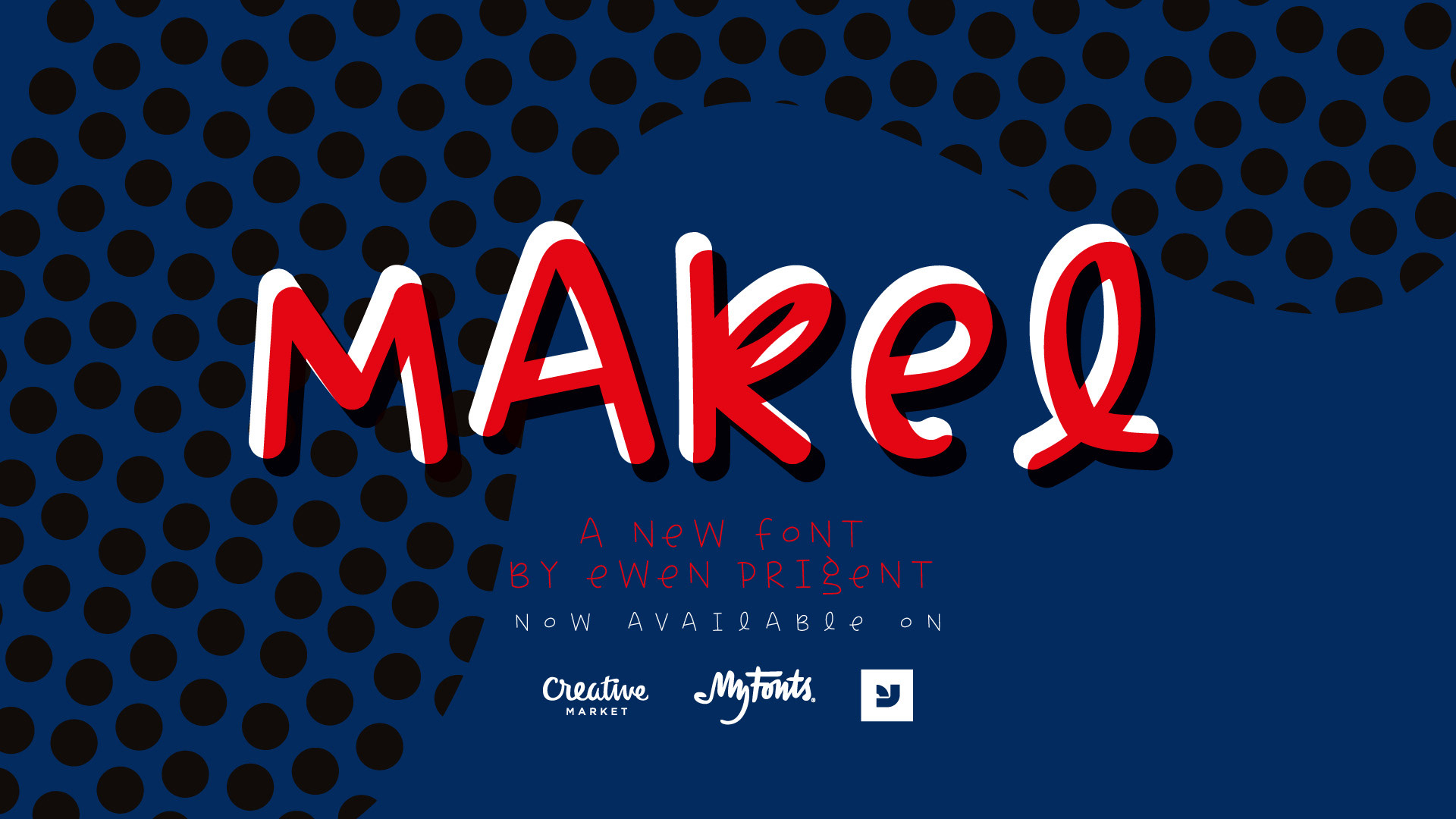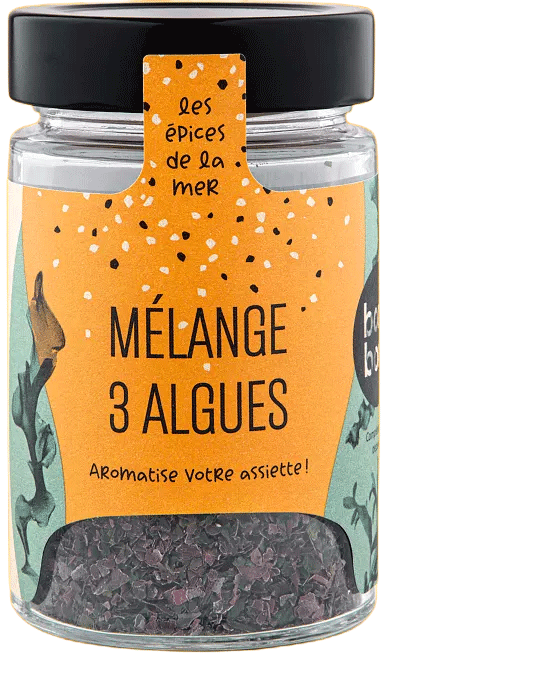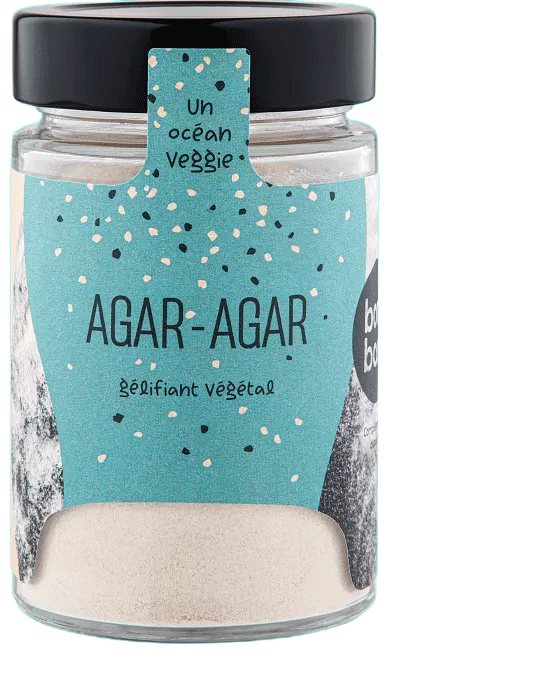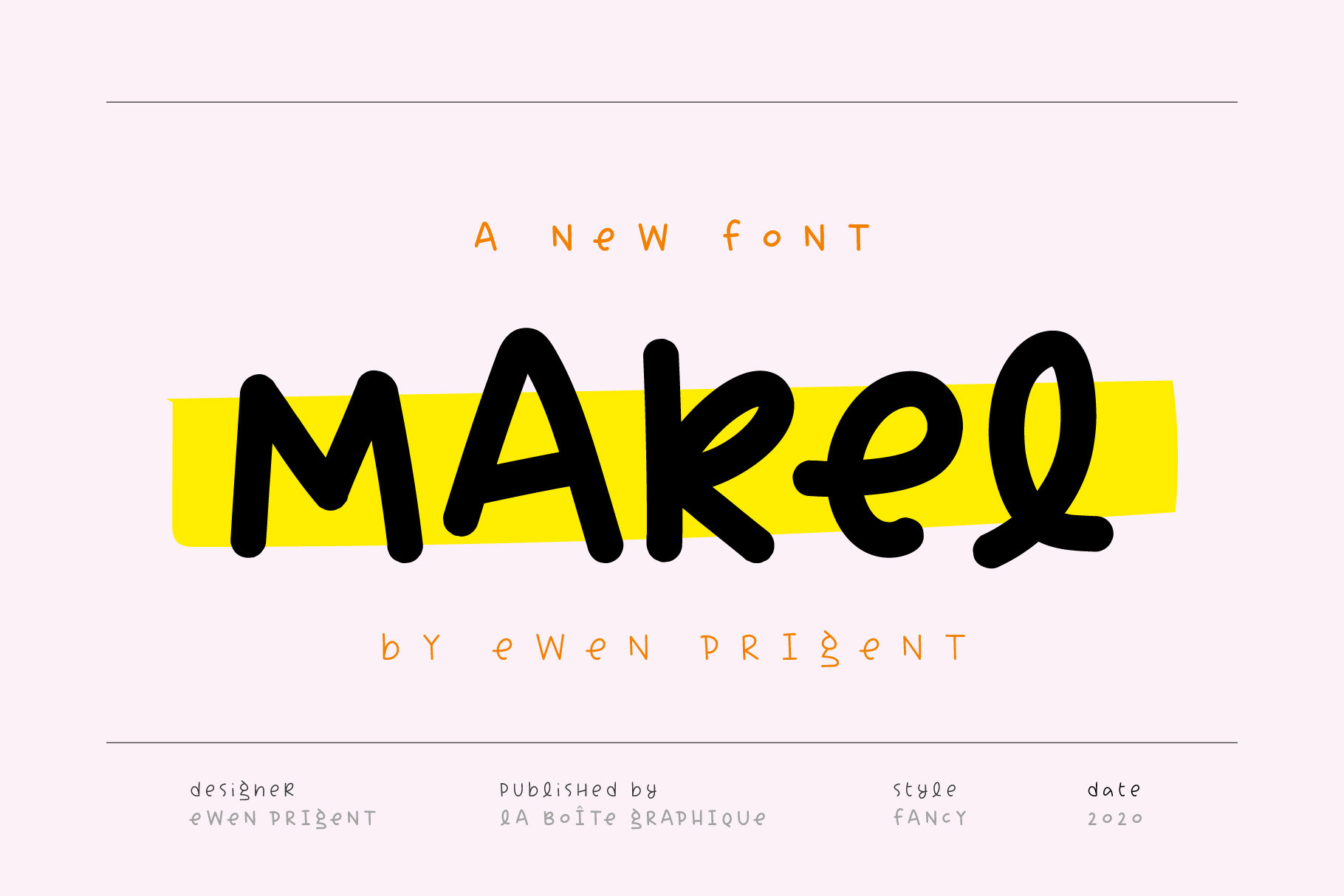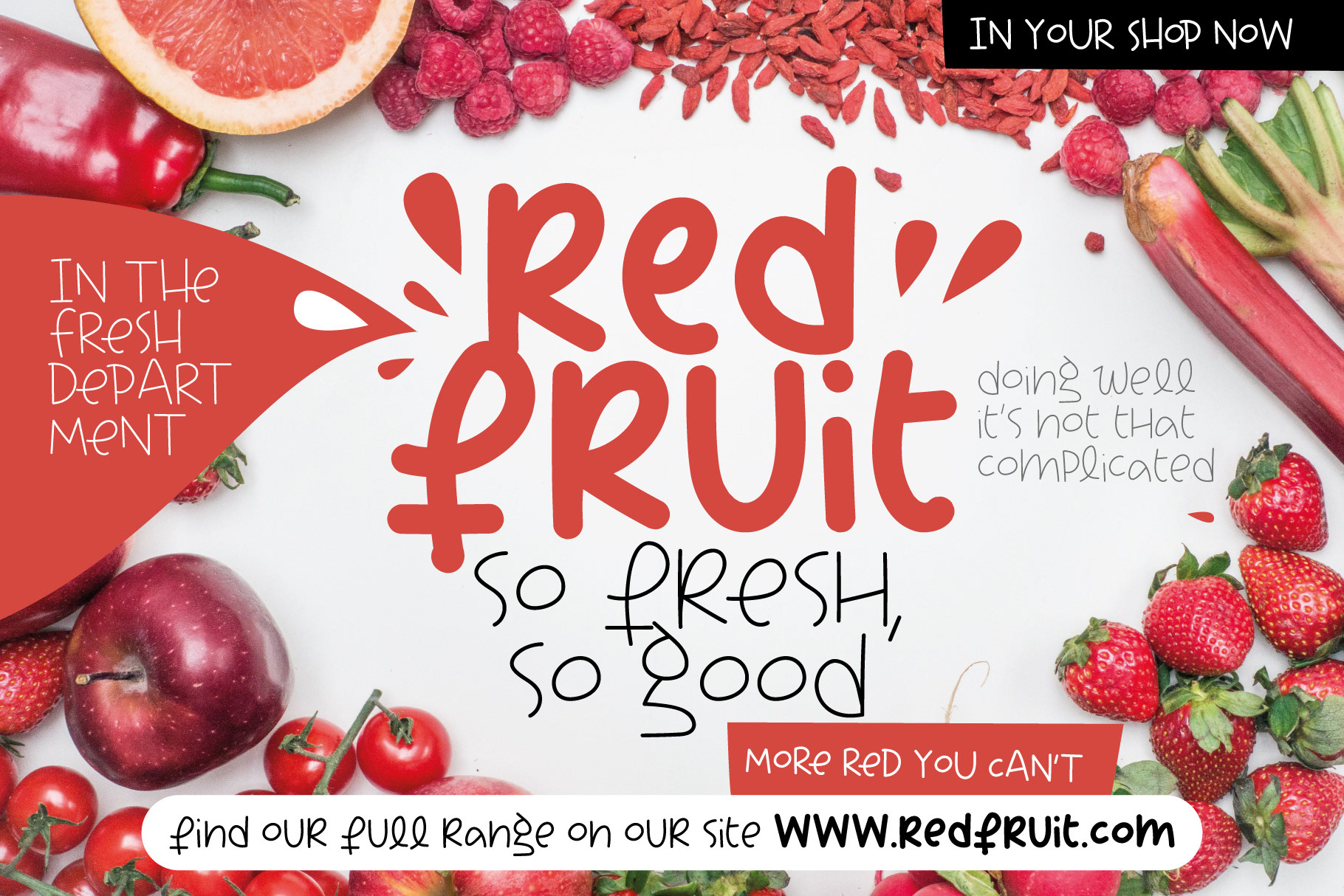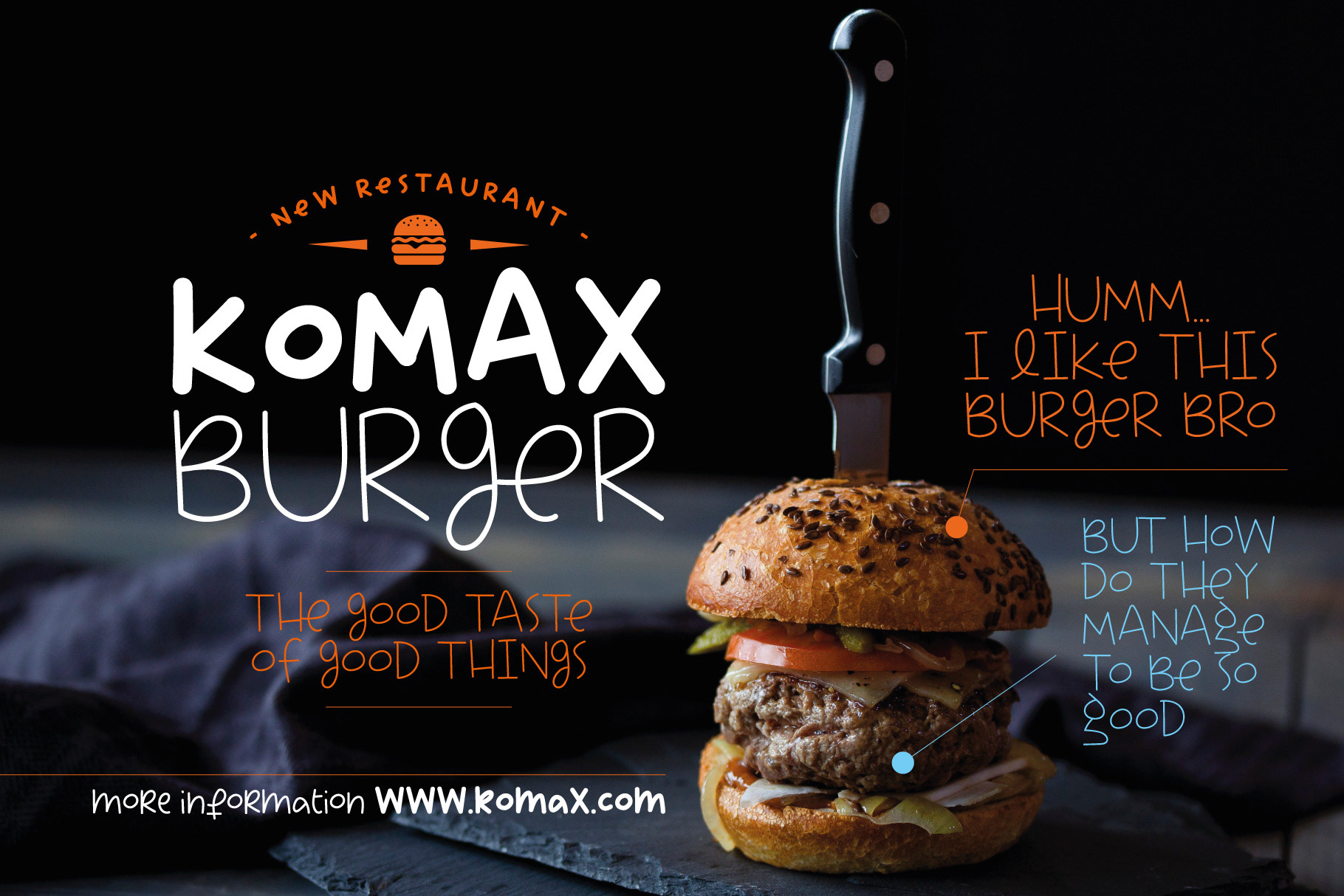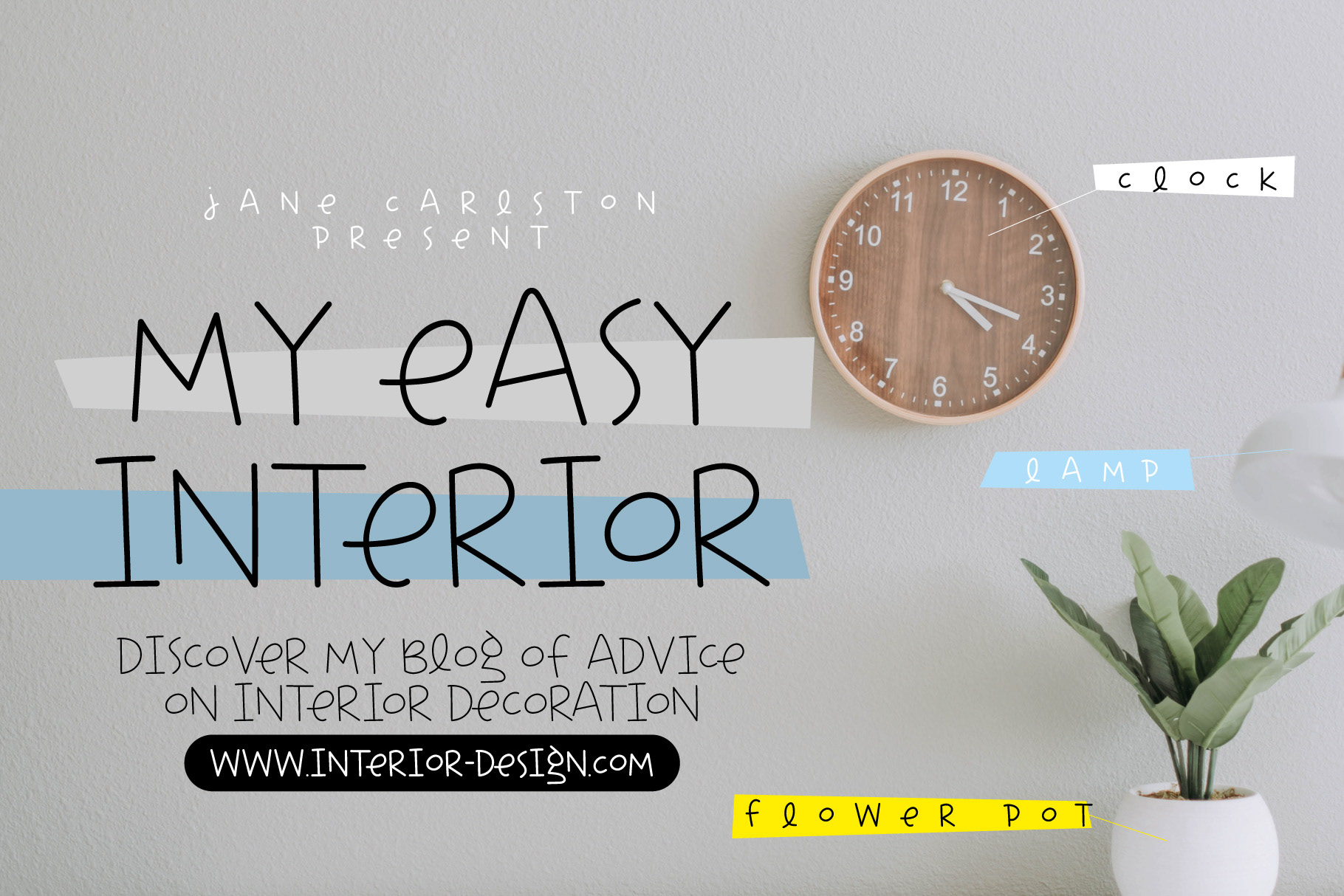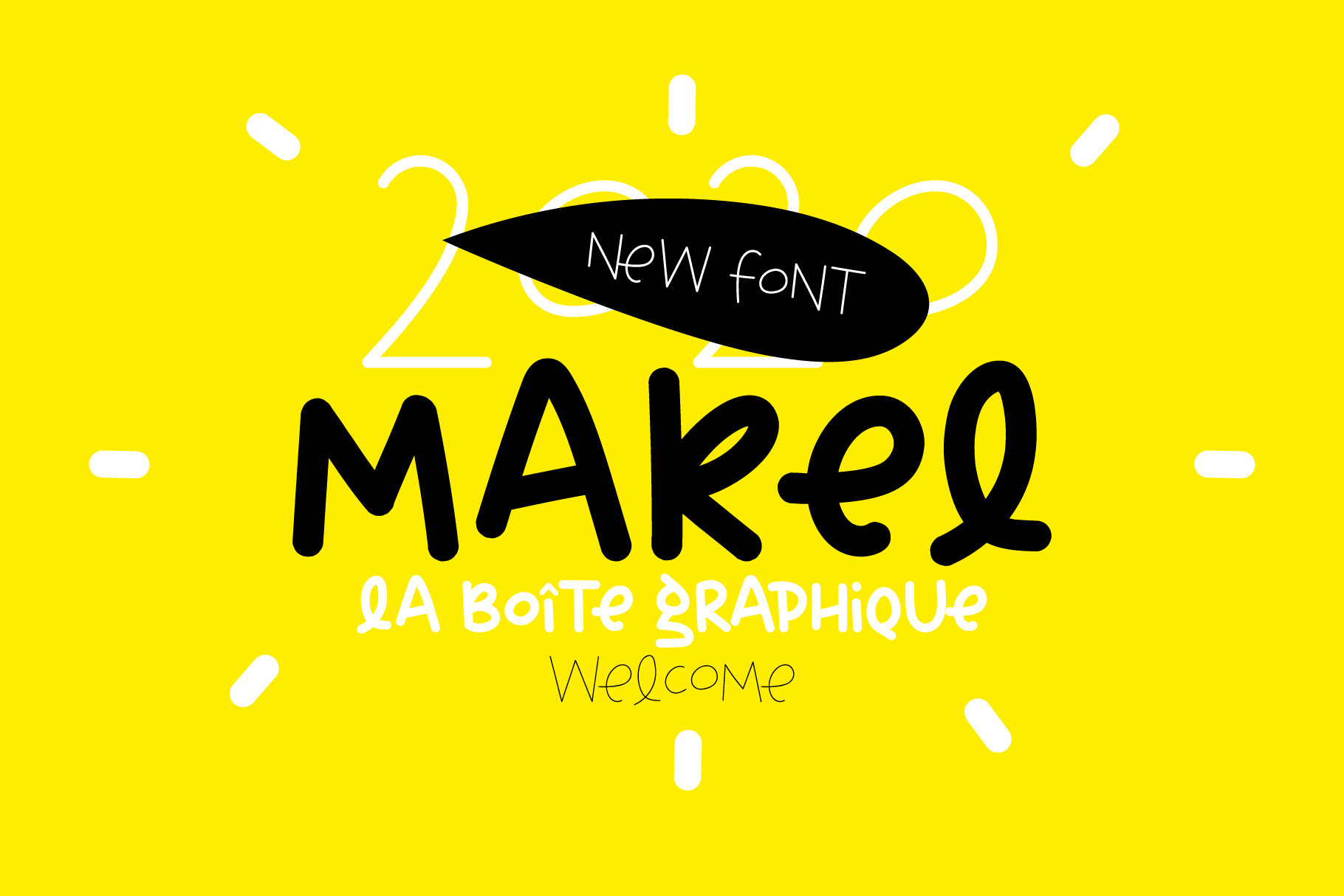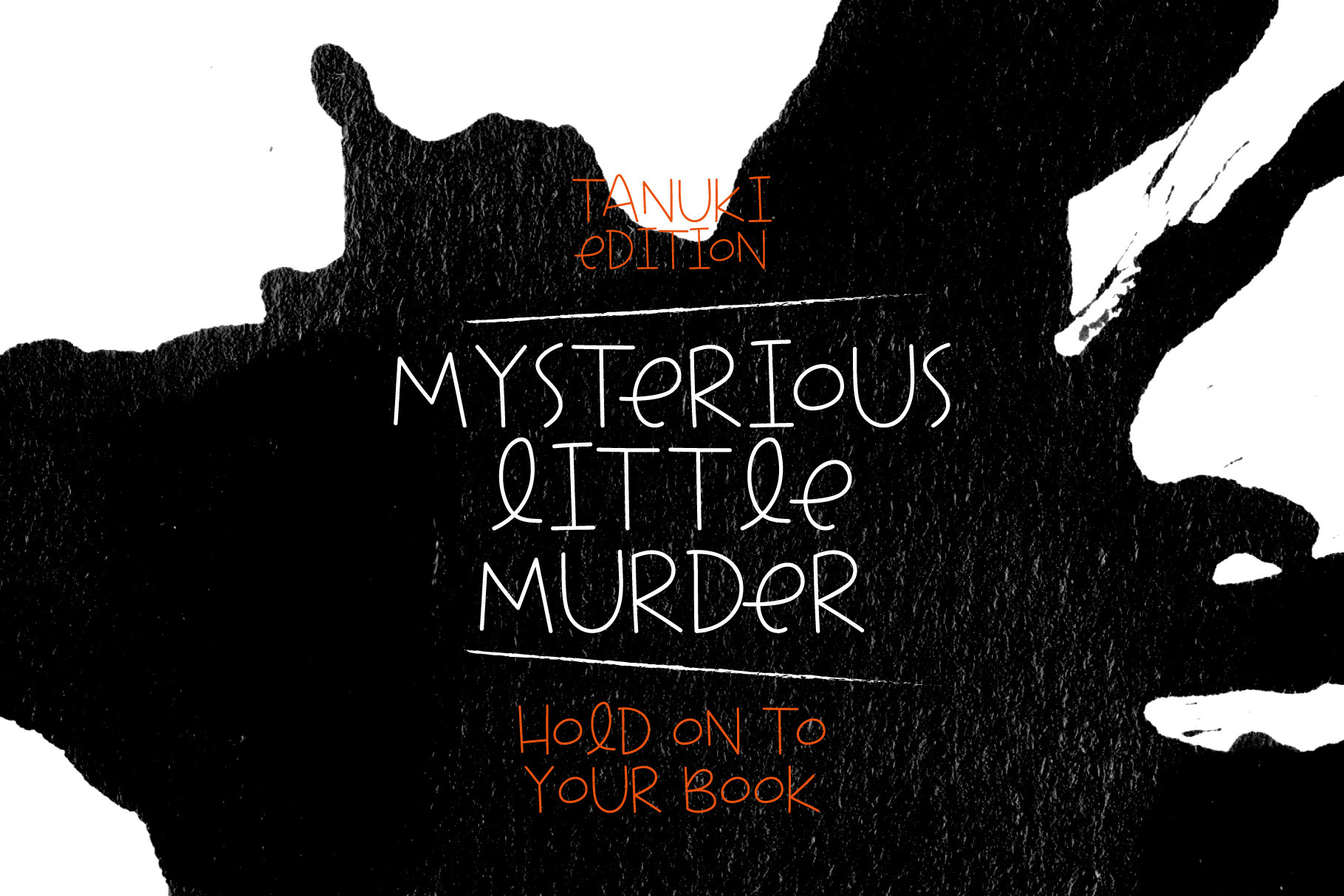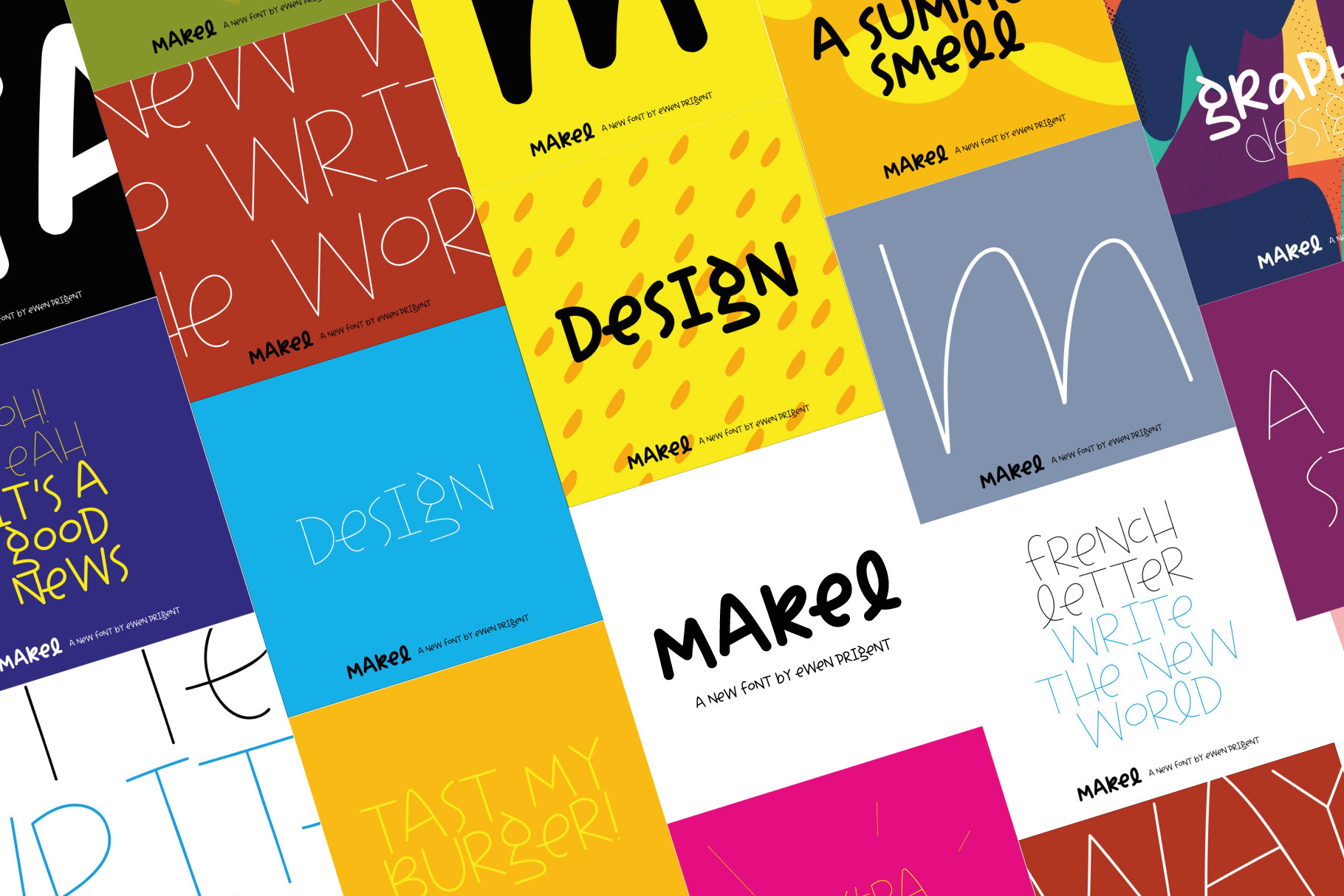
Makel est une typographie fantaisiste. Idéal pour des domaines tels que l'alimentaire, la restauration, le packaging, l'édition jeunesse… De part ses rondeurs et le mouvement des lettres, Makel souhaite apporter de la bonne humeur et du dynamisme à vos supports de communication.